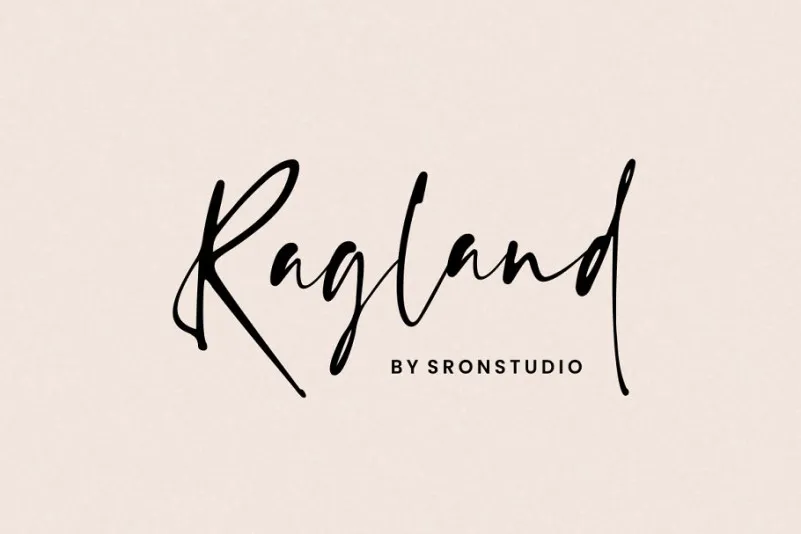
Ragland Handwritten Font – Fonte Grátis
Ragland Handwritten Font
A Ragland Handwritten Font é uma escolha perfeita para aqueles buscando personalidade e elegância em sua identidade visual. Desenvolvida pelo designer M.0Type, essa fonte script foi criada com um toque de sofisticação natural em suas linhas finas e delicadas, mantendo-se ao mesmo tempo amigável e confortável para leitura. Uma das características mais apreciadas da Ragland Handwritten Font é sua natureza handwritten. Com uma sensação de autenticidade que vem diretamente da arte do texto a mão, ela se destaca quando usada em aplicativos como logotipos, convites, materiais de papelaria, rótulos para embalagens, design editorial e publicações online. Essa fonte é especialmente adequada para criar um tom elegante no contexto de anúncios, embalagens de produtos ou mesmo para adicionar um toque personalizado em postes nas redes sociais. Com sua característica de ser uma fonte handwritten natural, ela oferece flexibilidade e versatilidade, tornando-a o tipo perfeito para diversos ambientes visuais que buscam criar um ar cuidadosamente pensado. Seja você criando um logotipo sofisticado ou estilizando os posts do seu blog para eventos especiais, a Ragland Handwritten Font é uma ótima opção. Com sua combinação única de elegância e conforto, ela se torna uma ferramenta valiosa em qualquer projeto gráfico que busque um ar refinado e autêntico.